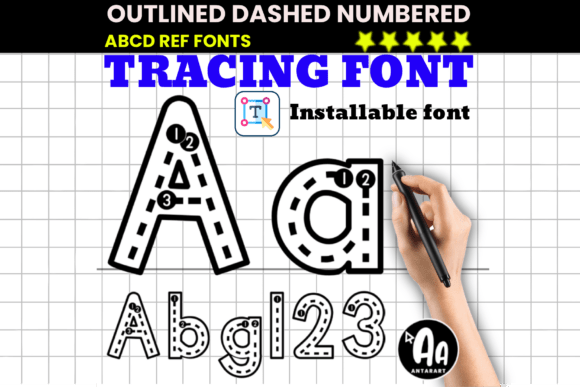
Outlined Dashed Tracing
Outlined Dashed Tracing – A Ferramenta Definitiva para Ensino de Caligrafia
Se você é professor ou educador que busca recursos interativos e divertidos para melhorar a caligrafia dos alunos, a coleção de fontes Outlined Dashed Tracing é a escolha perfeita. Desenvolvida especialmente para apoiar o ensino da formação de letras e números, esta fonte combina tracing (traçado) com criatividade, oferecendo materiais que estimulam a coordenação motora fina e o reconhecimento de símbolos.
Principais Benefícios
- Aprendizagem guiada: versões “Outlined‑Dashed” e “Outlined‑Dashed (Numbered)” apresentam linhas tracejadas e numeradas que indicam a ordem correta dos traços, facilitando a memorização muscular.
- Versatilidade total: inclui letras maiúsculas e minúsculas, números de 0 a 9 e símbolos comuns – tudo que você precisa para criar folhas de prática completas.
- Estímulo à criatividade: os contornos vazios permitem que os alunos coloram enquanto traçam, tornando o exercício mais lúdico e motivador.
- Ideal para material didático: perfeito para fichas imprimíveis, cartazes de quadro, decorações de sala, templates de nomes, revisões de volta às aulas e livros de caligrafia.
Como Usar na Sala de Aula
- Crie worksheets customizados com letras e números tracejados para que os alunos pratiquem o traçado correto.
- Utilize a versão numerada para ensinar a sequência de traços passo a passo, reforçando a memória muscular.
- Incorpore atividades de coloração: os estudantes podem pintar o interior das letras enquanto as traçam, desenvolvendo atenção aos detalhes.
- Monte quadros decorativos com as letras outline para inspirar a prática diária de escrita.
- Desenvolva fichas de revisão de alfabetização para o início do ano letivo, facilitando a transição de pré‑escola para o ensino fundamental.
Por que Escolher Outlined Dashed Tracing?
Baseada no tradicional estilo de caligrafia escolar, esta fonte oferece estrutura e diversão em um só pacote. Embora não suporte caracteres em espanhol, cobre todo o alfabeto português, permitindo que professores criem recursos totalmente adaptados ao currículo nacional. Ao investir nesta fonte, você garante: